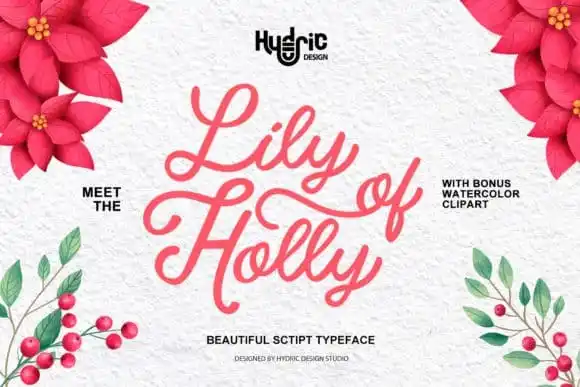
Lily Of Holly Calligraphy Font – Download Grátis
A Lily Of Holly é uma fonte script que traz a atmosfera festiva do Natal com sua beleza elegante e delicada. Este design contém linhas curvas e finas, criando um estilo gráfico suave e único, perfeito para ilustrar diversos projetos de design. Com seu charme luminoso, a Lily Of Holly é uma escolha ideal tanto para nomes de livros ou novelas quanto para títulos de filmes. É também uma ótima opção para marcas, logomarcas e identidades de marca. A fonte se adapta perfeitamente à publicidade, posts nas redes sociais e designs de produtos. Sua personalização única torna o texto do seu design mais atraente e único, permitindo que você ofereça sua marca uma aparência encantadora no Natal ou qualquer outro momento especial. Com a Lily Of Holly Calligraphy Font, seus projetos ganharão um toque adicional de estilo elegante durante esta época do ano. Ideal para quem busca trazer um ar de festa e sofisticação a suas criações gráficas, essa fonte é uma excelente opção para designers e criativos. Aproveite-a em seu próximo projeto!